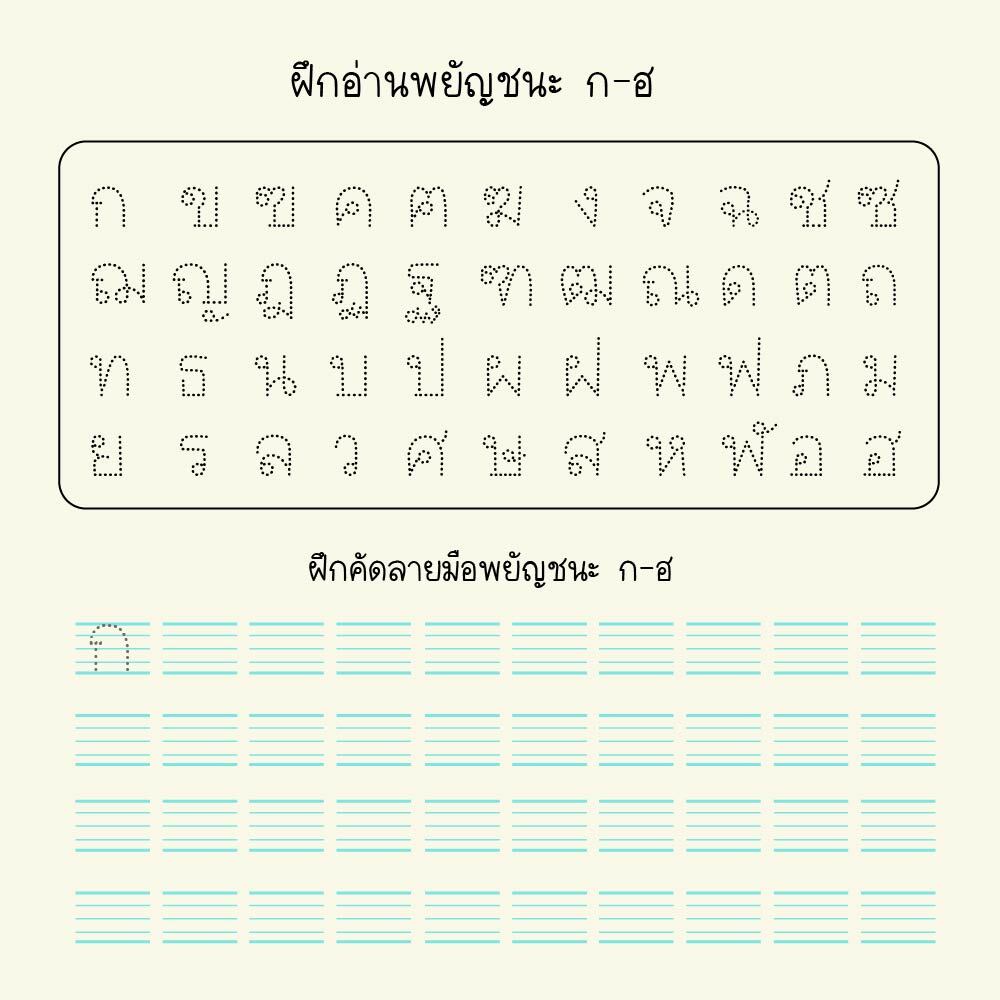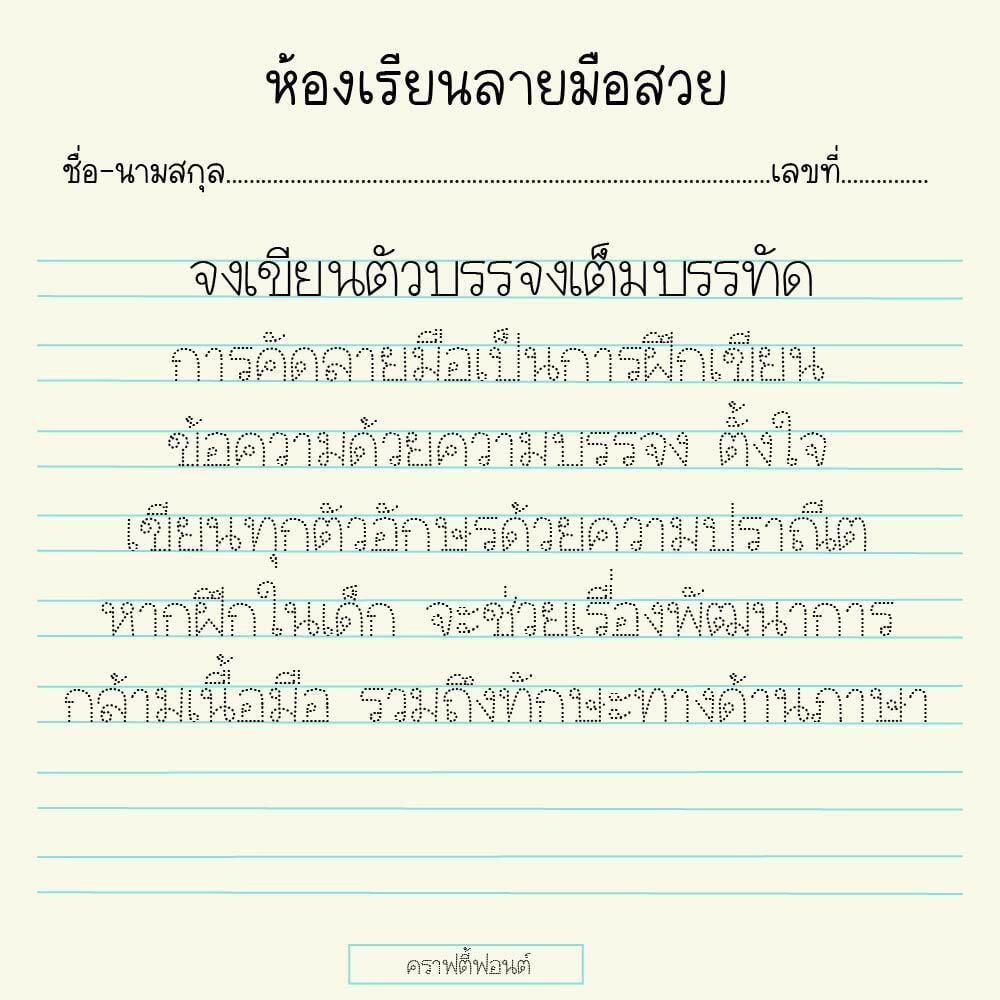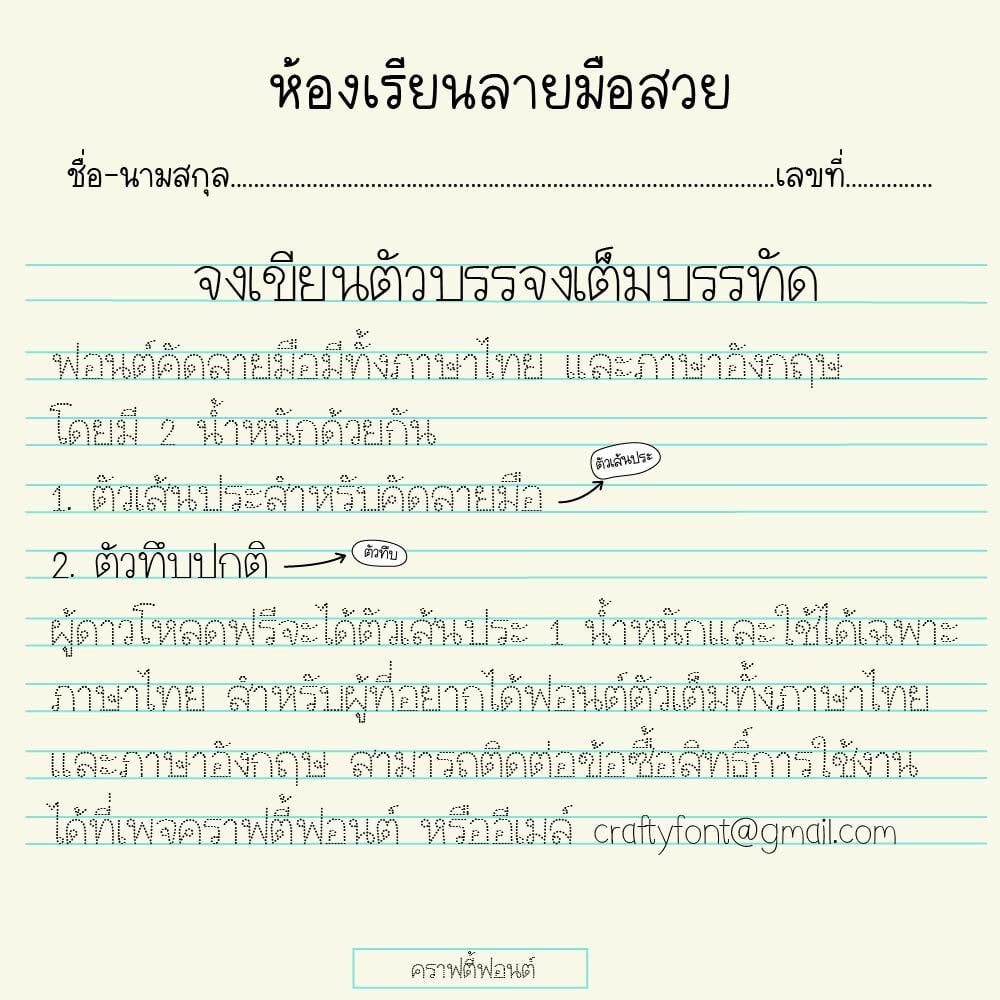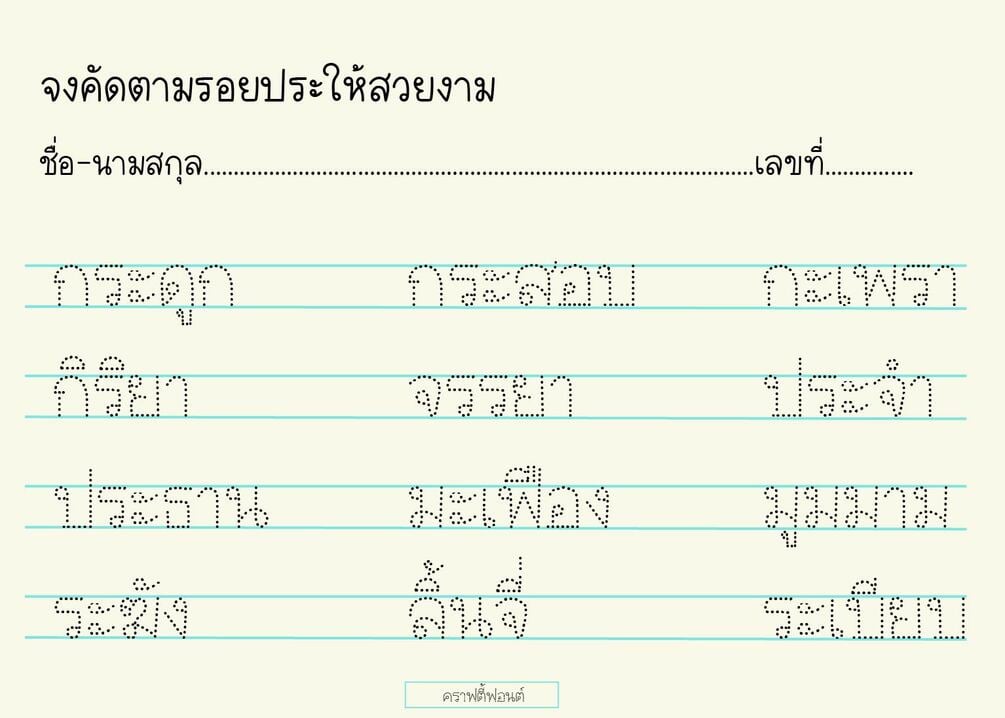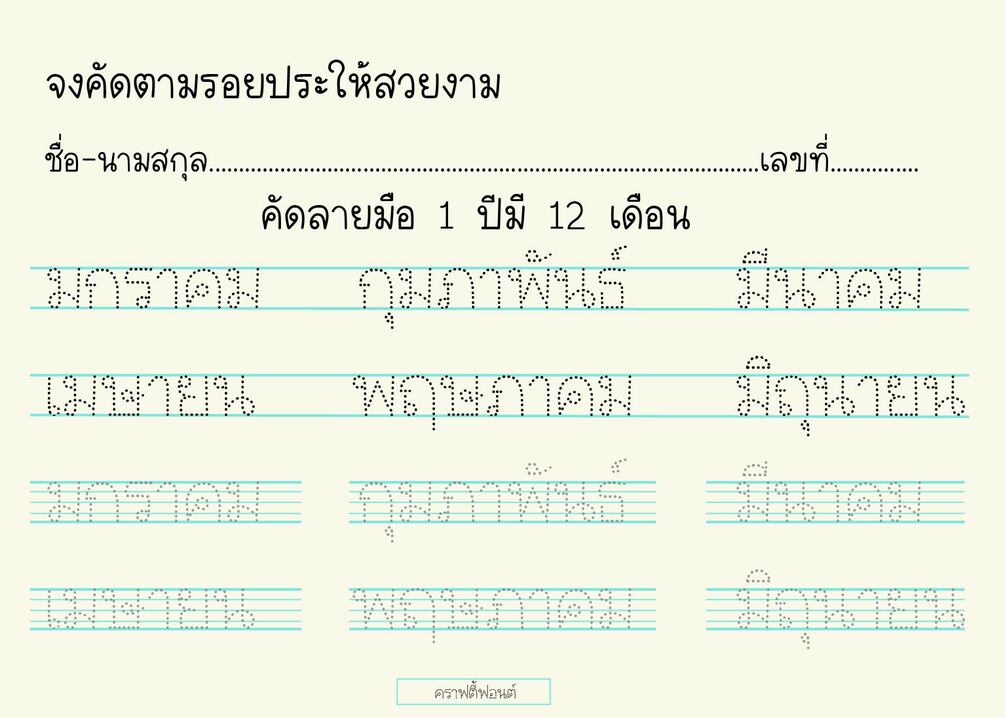
Kudlaimue Font (ฟอนต์คัดลายมือ)
ฟอนต์คัดลายมือ การคัดลายมือเป็นการฝึกเขียนข้อความด้วยความบรรจง ตั้งใจเขียนทุกตัวอักษรด้วยความปราณีต หากฝึกในเด็ก จะช่วยเรื่องพัฒนาการกล้ามเนื้อมือ รวมถึงทักษะทางด้านภาษา เหมาะมากสำหรับคุณครูชั้นอนุบาล หรือปฐมศึกษาตอนต้นค่ะ